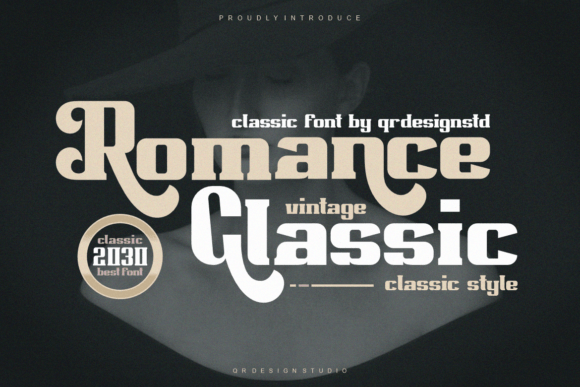
Romance Classic
Ulasan Lengkap: Font Romance Classic – Elegansi dan Kekuatan dalam Setiap Teks
Si Anda sedang mencari font yang mampu memadukan kekuatan klasik dengan sentuhan modern, Romance Classic adalah pilihan yang tepat. Font serif berani ini dirancang untuk memberikan kesan otentik, namun tetap fleksibel untuk berbagai aplikasi, mulai dari logo, pencetakan kaos, hingga branding e‑sport. Berikut ulasan lengkap tentang keunggulan, keunikan, dan cara optimal menggunakan Romance Classic.
Keunggulan Utama Romance Classic
- Bold dan Autentik – Garis tebal dan bentuk serif tradisional menciptakan tampilan yang kuat dan berkesan.
- Fleksibilitas Tinggi – Cocok untuk branding logo, kaos, poster, dan media digital seperti game dan e‑sport.
- Visibilitas Ekstra – Desainnya membuat teks tetap terbaca di berbagai ukuran, baik di papan nama maupun di layar kecil.
- Estetika Universal – Mampu menyesuaikan diri dengan banyak gaya desain, dari minimalis hingga klasik‑modern.
Bagaimana Romance Classic Meningkatkan Brand Anda
Dalam dunia pemasaran yang kompetitif, identitas visual yang kuat adalah kunci. Romance Classic menawarkan:
- Penguatan Brand Identity – Memberikan kesan premium dan berkelas.
- Keseragaman Visual – Memudahkan pembuatan materi promosi yang konsisten.
- Pengaruh Emosional – Serif klasik memicu rasa nostalgia dan kepercayaan.
Kesimpulan
Romance Classic bukan sekadar font; ia adalah alat branding yang kuat, menggabungkan estetika klasik dengan daya tarik modern. Baik Anda mendesain logo perusahaan, mencetak kaos fanklub, atau membuat banner e‑sport, font ini akan memberikan tampilan yang menonjol dan profesional. Dengan memasukkan Romance Classic ke dalam strategi desain Anda, Anda tidak hanya menambah nilai estetika tetapi juga meningkatkan konsistensi merek dan pengalaman pengguna.